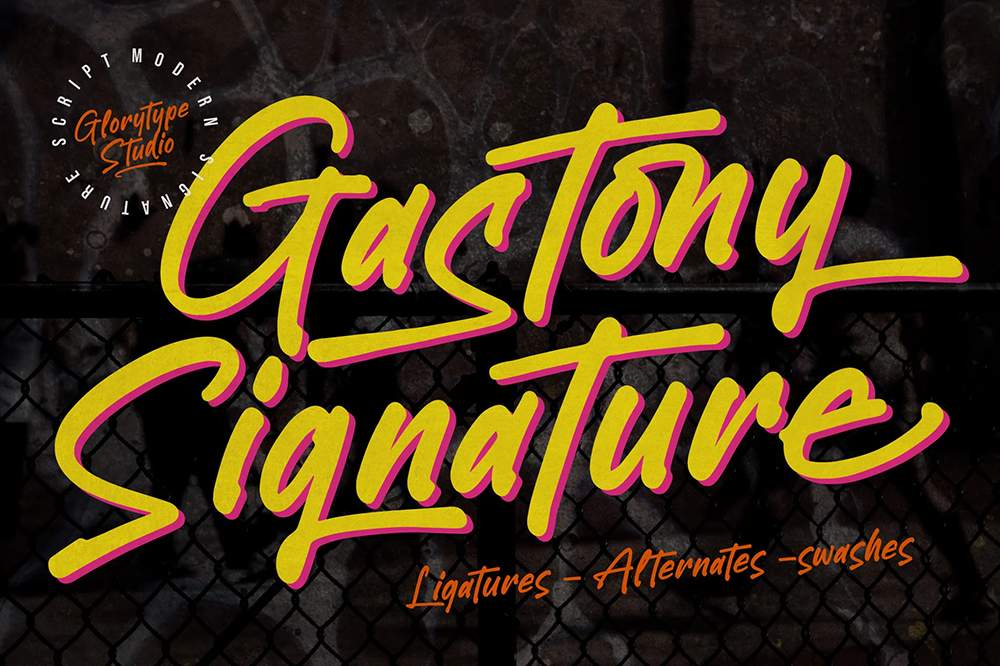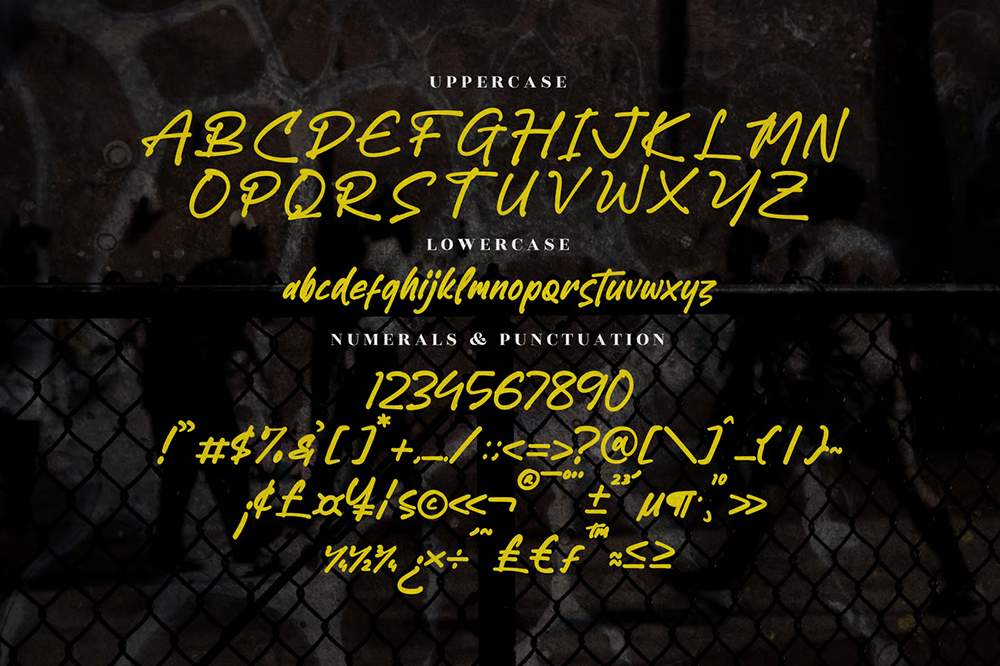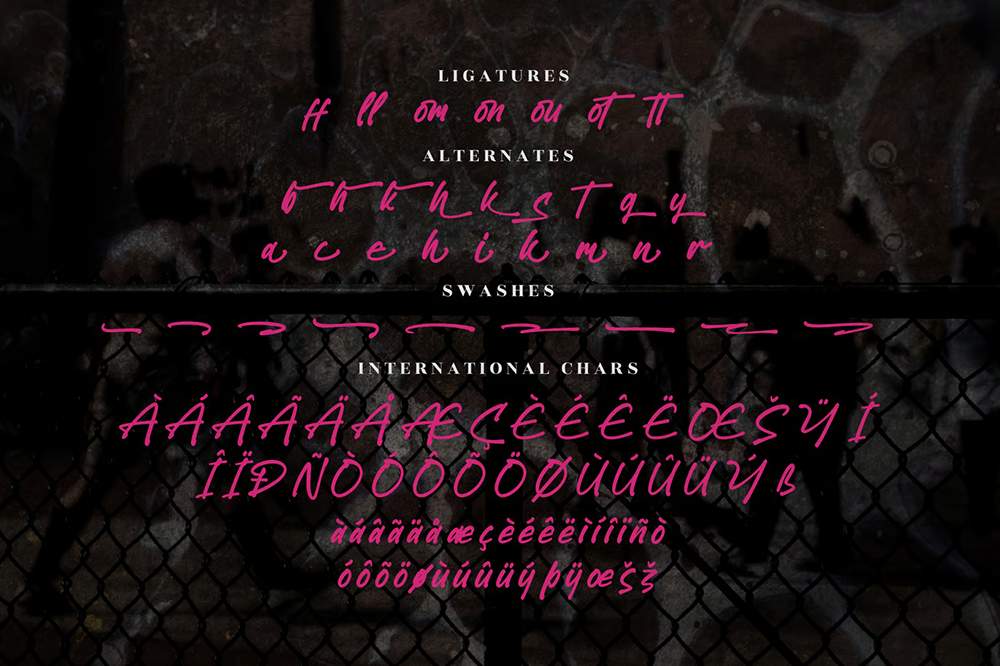
فونت پرمیوم و انگلیسی Gastony Signature Font يک فونت امضادار جسورانه و رسا است که برای ايجاد شخصيتی پرانرژی و دستساز به طرحهای شما ايجاد شده است. اين فونت با خطوط ضخيم، جريان پويا و سبک شهری مدرن، تأثير بصری قویای ارائه میدهد و برای پروژههايی که به نگرش، هويت و ذوق هنری نياز دارند، ايدهآل است.
مزایای استفاده از فونت لاتین Gastony Signature چیست؟